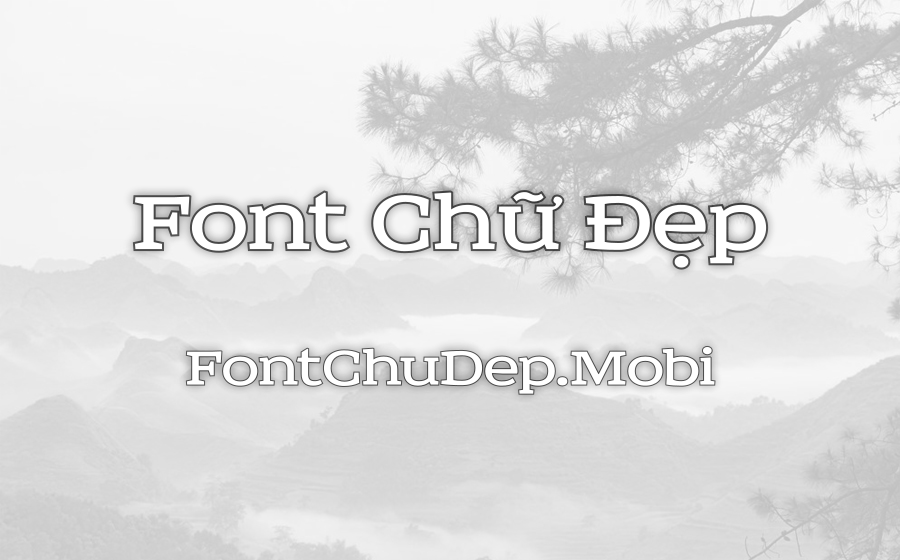
Font UVF Sreda Việt Hóa
UVF Sreda
Sreda là một font chữ do Glenjan thiết kế, nổi bật với 665 ký tự đa dạng, tạo nên sự linh hoạt đáng kinh ngạc cho mọi dự án thiết kế. Font này đã được Việt hóa hoàn toàn, hỗ trợ đầy đủ các ký tự tiếng Việt, giúp người dùng tại Việt Nam dễ dàng tích hợp nó vào những sản phẩm sáng tạo của mình mà không gặp bất kỳ trở ngại nào.
Ngay khi trải nghiệm Sreda, tôi đã bị cuốn hút bởi thiết kế độc đáo và nghệ thuật của nó. Font này thực sự là một lựa chọn hoàn hảo cho những ứng dụng đòi hỏi sự sang trọng và chuyên nghiệp như thiệp mời, logo thương hiệu cao cấp hay bìa sách. Nó mang lại một cảm giác mạnh mẽ về thị giác và khơi gợi cảm xúc sâu sắc, làm cho mọi thiết kế trở nên ấn tượng và khó quên.
Không chỉ giới hạn ở những ứng dụng trên, Sreda còn là sự lựa chọn lý tưởng cho các sự kiện quan trọng như lễ hội, lễ cưới hay các dịp văn hóa đặc biệt. Khả năng thích ứng của font này với những ngành nghề sáng tạo như thiết kế đồ họa, nghệ thuật trang trí và xuất bản thực sự đáng kinh ngạc. Với FontChuDep.mobi, bạn có thể dễ dàng khám phá và áp dụng Sreda một cách tối ưu nhất cho mọi dự án yêu thích của mình.